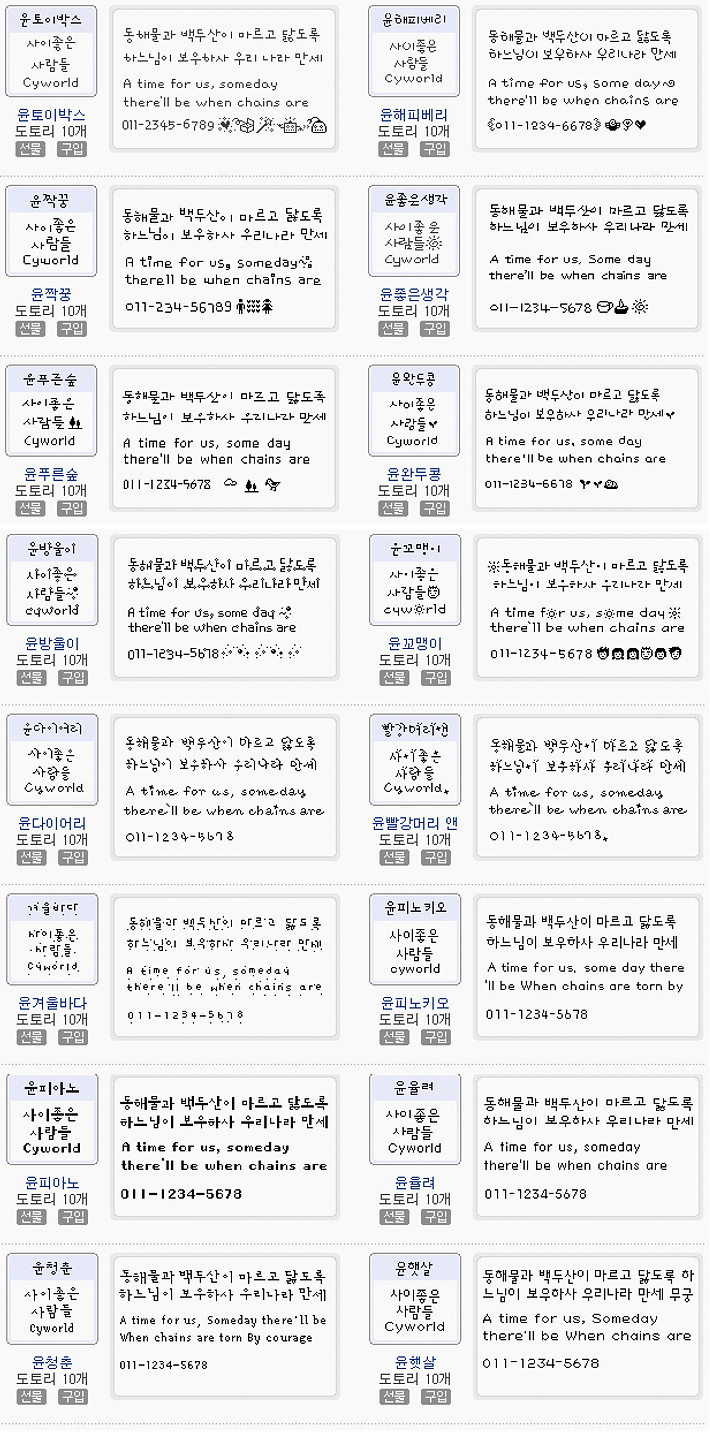
선생님들.... 지금 일주일 째 이 폰트를 찾느라 인터넷 세상 속에 갖혀버린 사람입니다.. 눈누..한글..윤고딕..모리스.. 구글.. ai... 여기저기.. 다 돌아다녀도 안나옵니다 ㅠㅠ 제발 찾아주십쇼오 ㅠㅠㅠㅠㅠ
싸이월드 폰트체
싸이월드 웹폰트나 옛날 핸드폰 폰트 같아요! 싸이월드 웹폰트 같은 건 종류가 너무 많고 서버가 종료돼서 똑같은 거 찾기가 어렵네요..! 싸이월드 글꼴 검색해보시면 비슷한 느낌 많이 나와요